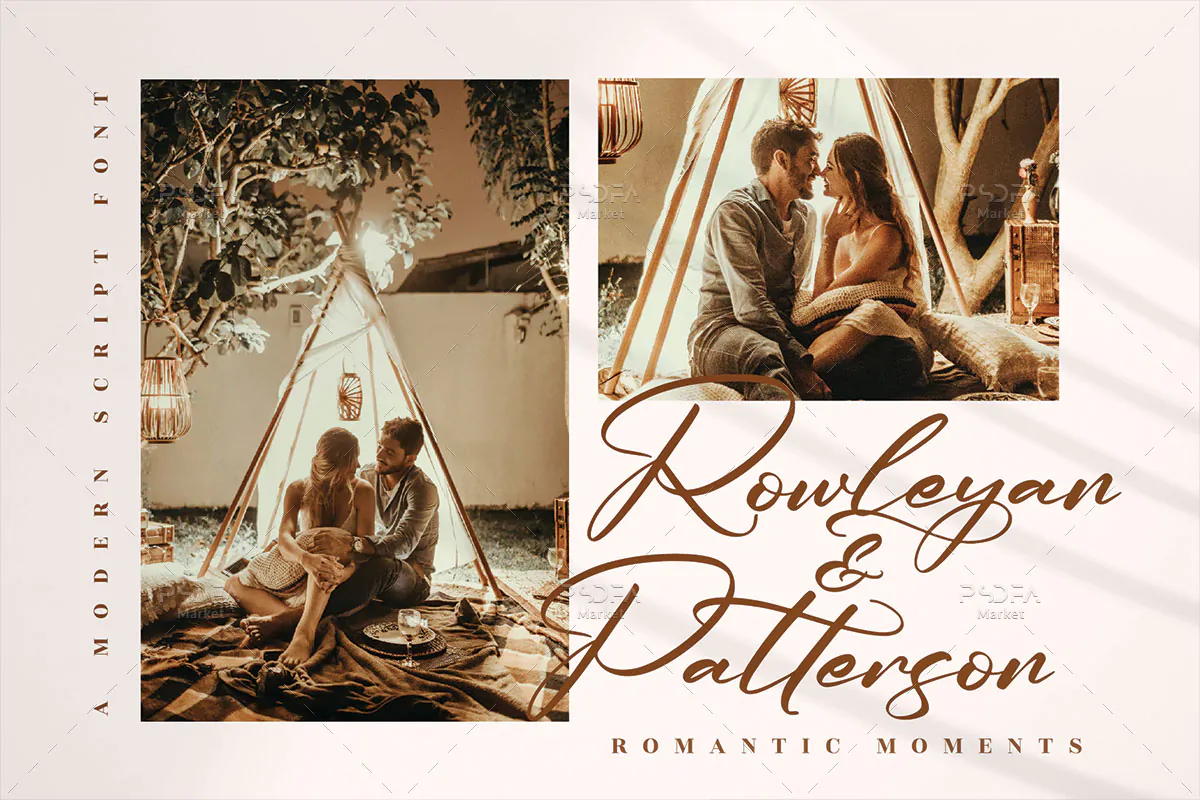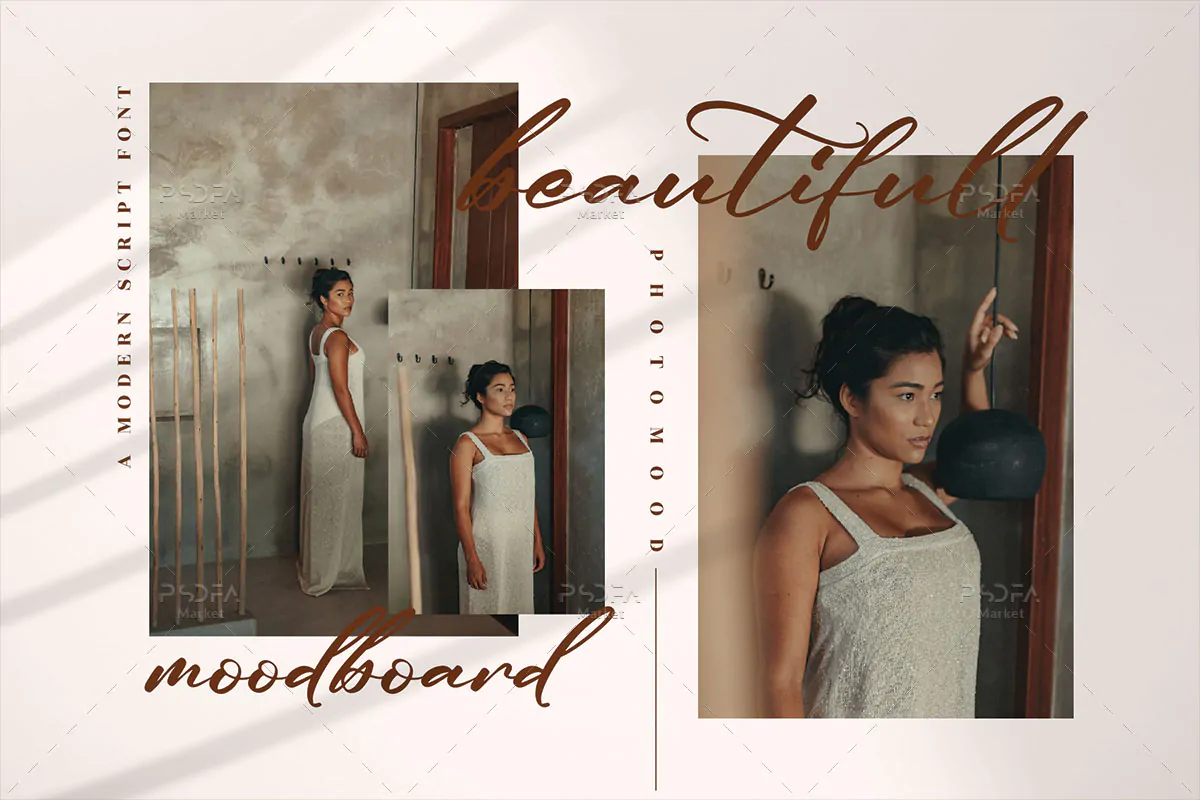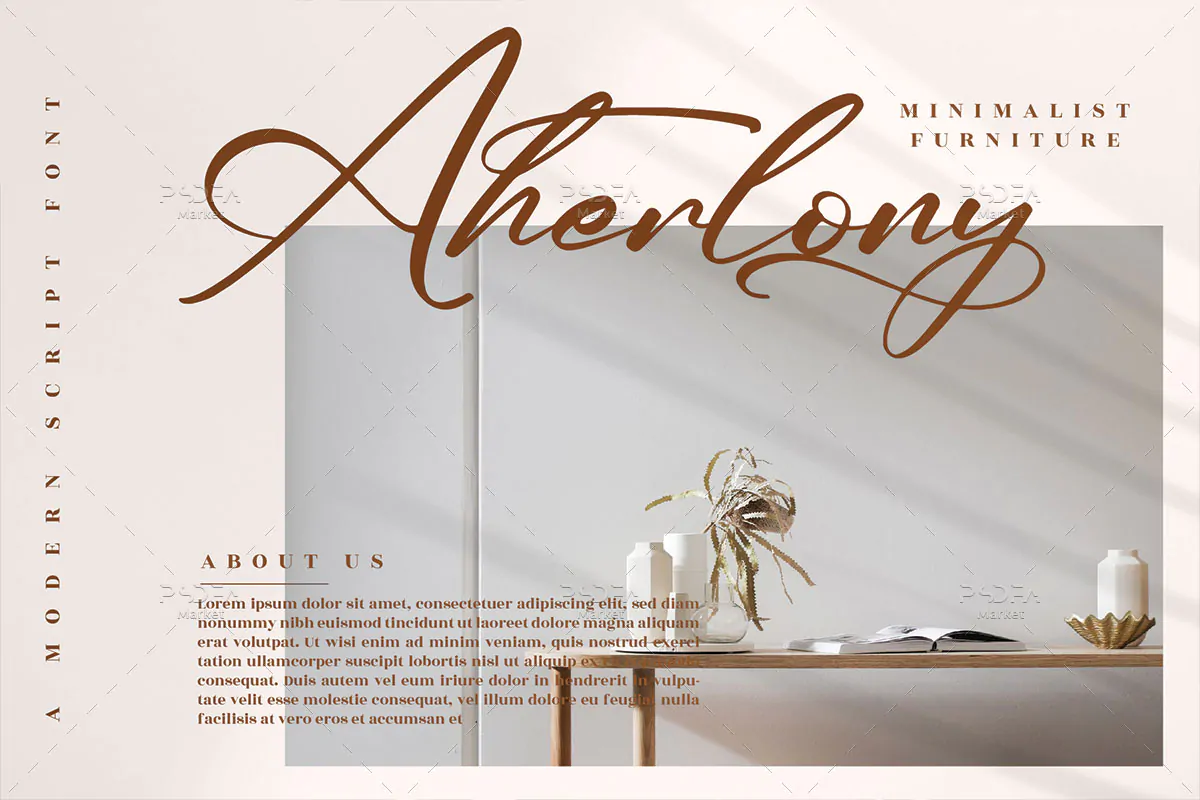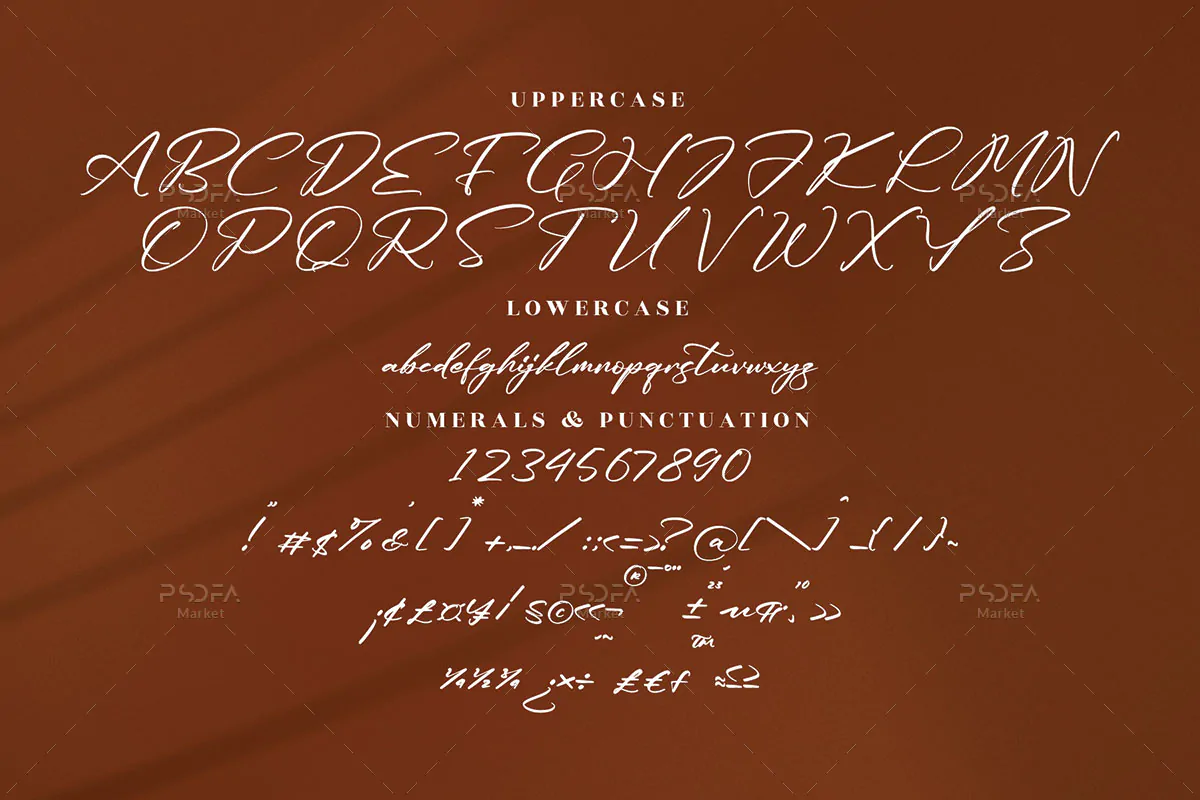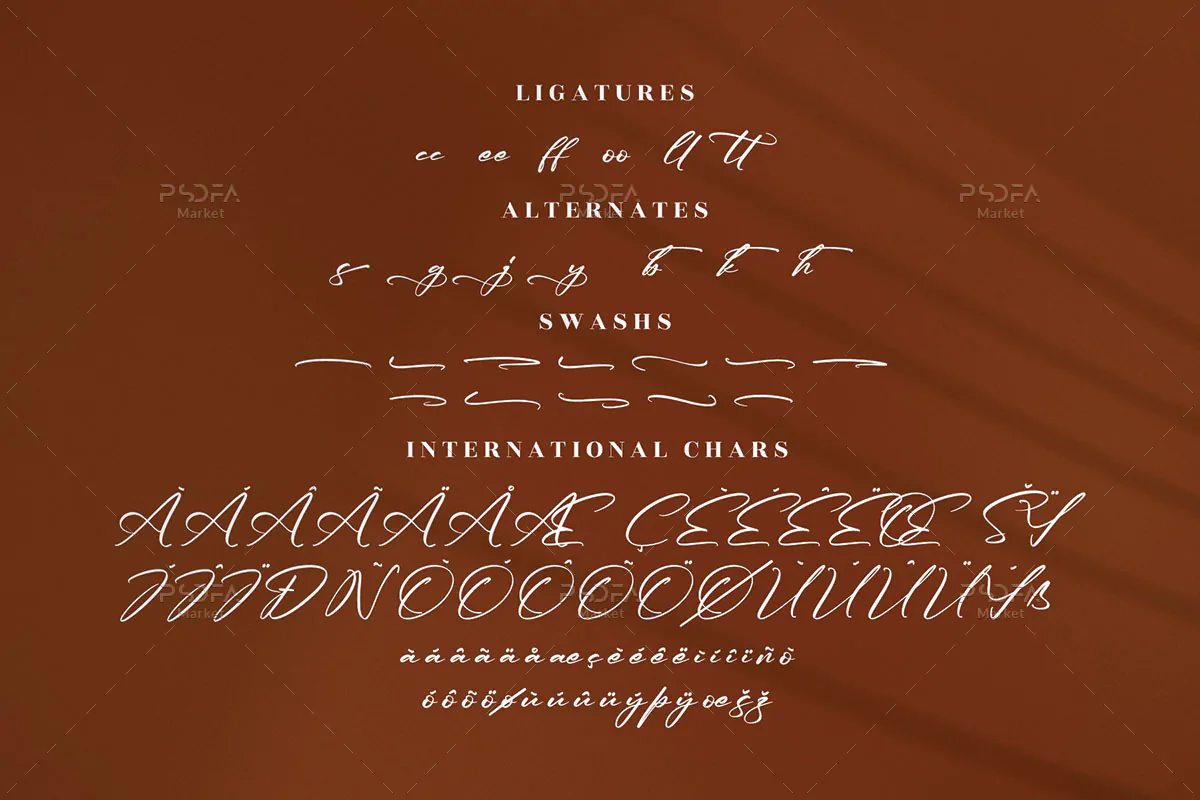
فونت دستنویس مدرن Sandiago
فونت دستنویس مدرن
فونت دستنویس مدرن Sandiago یک اسکریپت فونت فوق العاده زیبای انگلیسی است که مناسب جهت استفاده در طرح و پروژههای گرافیکی مختلف میباشد. فونت Sandiago با دو وزن معمولی و مورب طراحی شده است که میتوانید از آن در طراحی انواع کارتهای تبریک، کارت عروسی، طرحهای رمانتیک و عاشقانه، بسته بندی محصولات، آرایشی و بهداشتی، لوازم التحریر و … استفاده کنید.